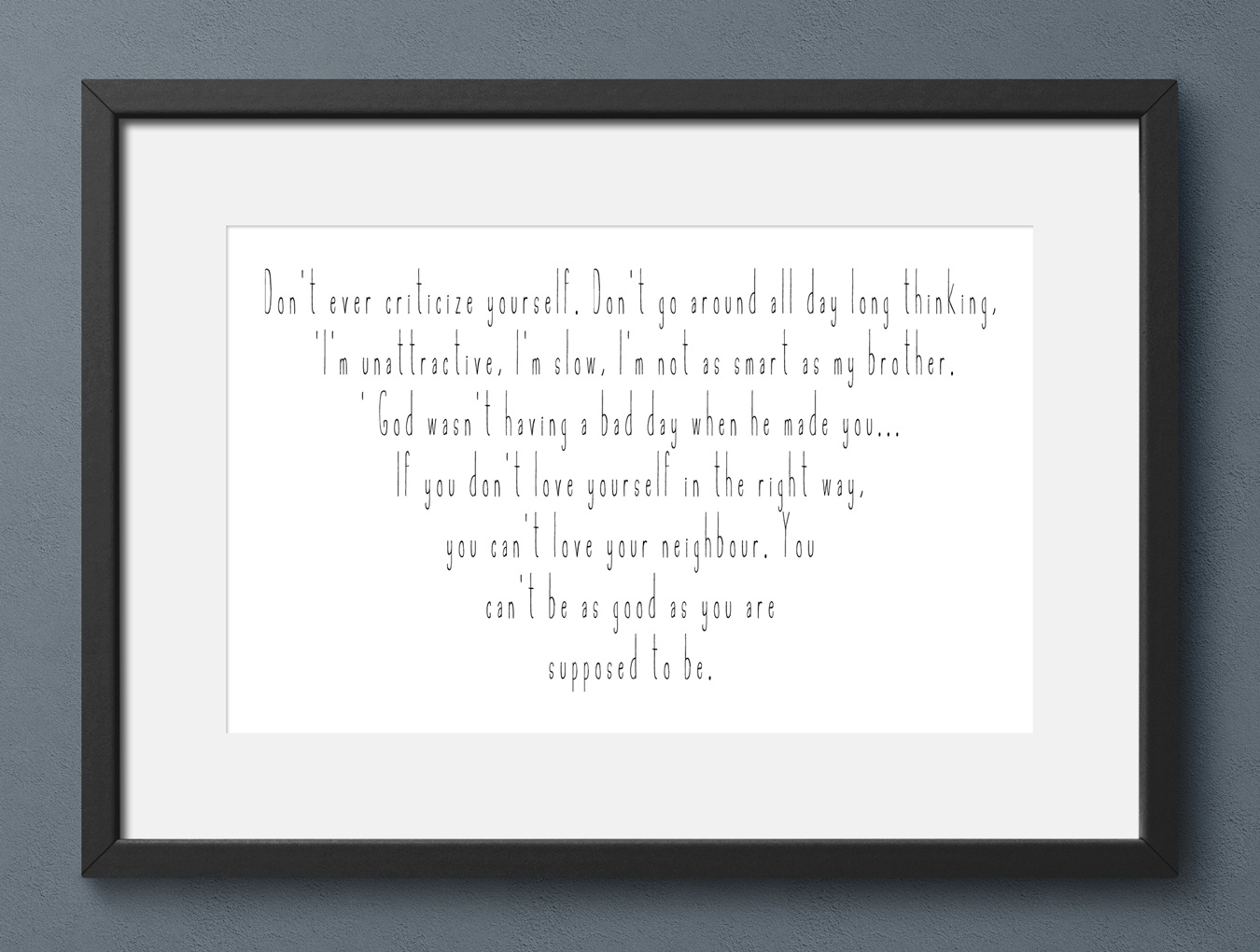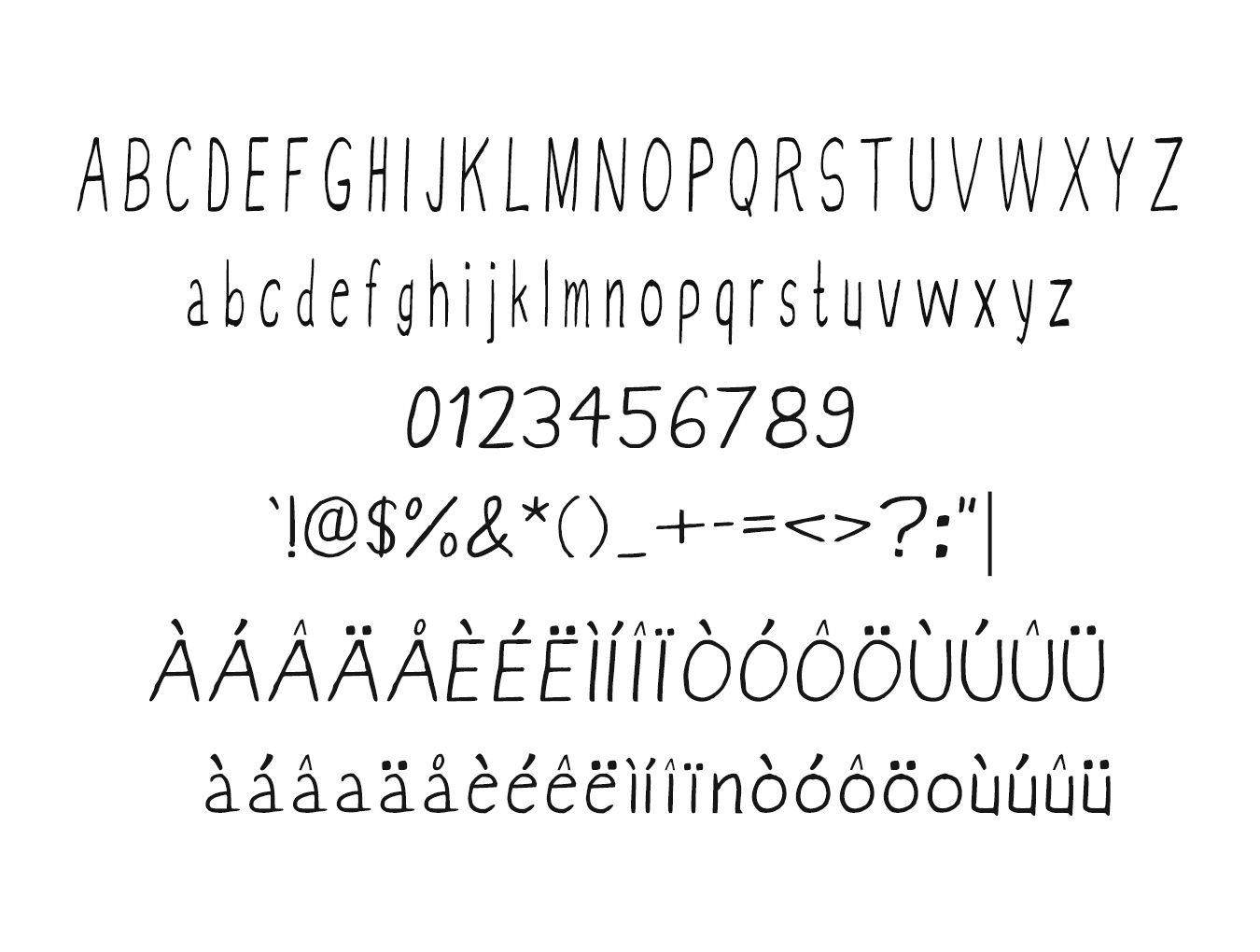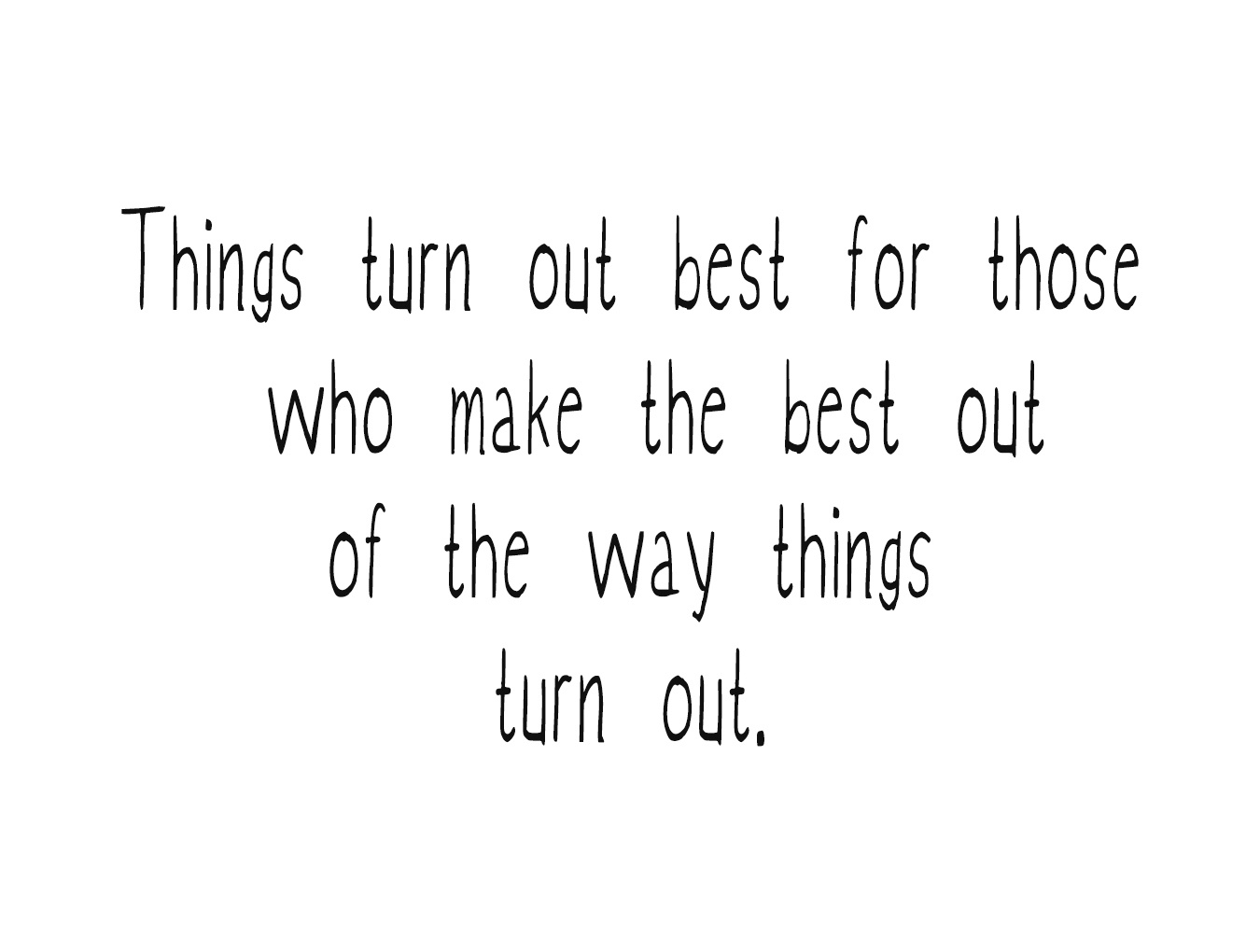
双手工制作的脚本字体和奖金剪贴画。,Vannah字体二重奏
Vannah Font Duo是一个双手工制作的脚本字体,包含大小写字母,数字和一串标点符号。如果你想尝试一个优雅的外观,这些字体在所有大写间距看起来都很棒,或者在大写字母和小写字母中完美无缺。非常适合设计手写报价,品牌和徽标项目,商品,社交媒体帖子,展示,标题,邀请,保存日期,婚礼,标题,产品包装等。